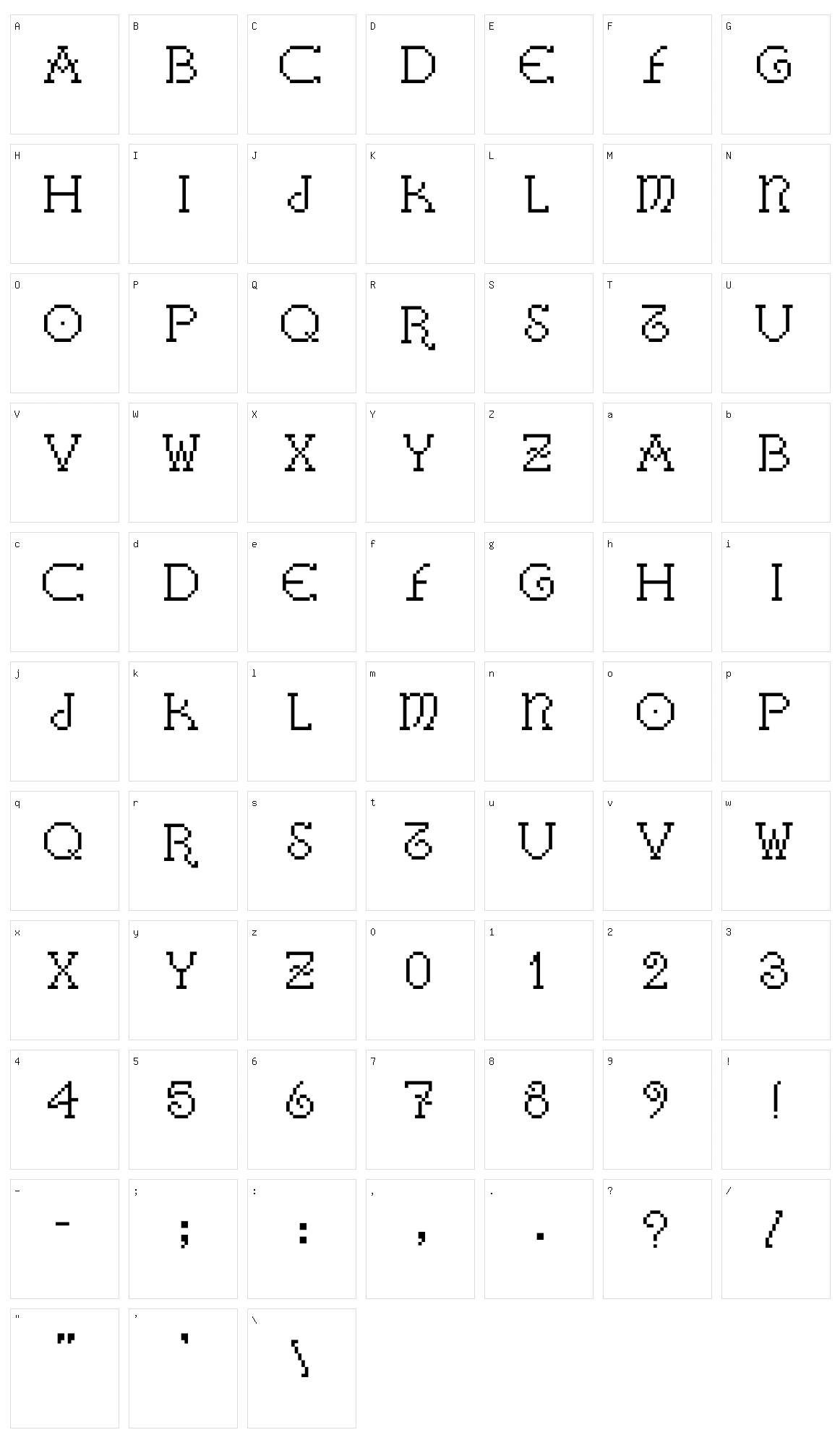
Gallaecia Pixeleira
Designed by: David Calvi?o
[][][] GALLAECIA PIXELEIRA [][][]
Por David Calviño
Gallaecia Pixeleira é unha adaptación a estilo pixel da tipografía Gallaecia Castelo deseñada por Carlos Nuñez.
Made by David Calviño
Gallaecia Pixeleira is a pixel adaptation of Gallaecia Castelo Font, originally designed by Carlos Nuñez.